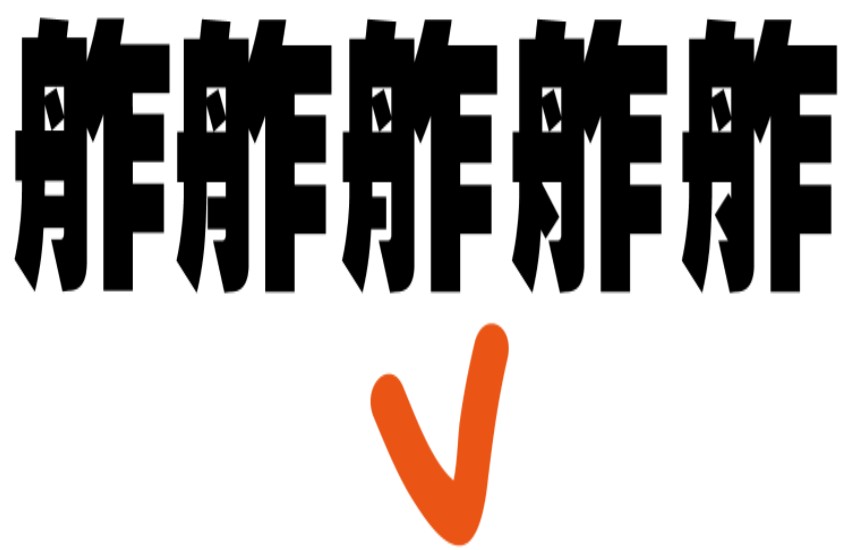
逐浪经典粗黑体
作品设计背景与理念
逐浪经典粗黑体是一种基于现代汉字简体设计的字体,力求创造一种特粗黑体。
我们看到市面上的粗黑体有以下问题:
1. 粗壮而无细节,缺乏韵的美;
2. 违反中国书法的传统原则;
3. 可选空间较少,甚至形成了“粗就是丑”、“丑必然粗”的悖论。
于是逐浪软件人启动了本字库的研发。
设计本字库时,我们确定了字体(库)研发八步原则:
1、选样本
2、建规则
3、创模板
4、开工厂
5、勾字形
6、导字库
7、发软件
8、测版面
与传统粗黑字体相比,逐浪经典粗黑体的特色细节包括:
左边“又”字、反文旁的字,最后一笔角度拉大,使之更有力量。
红等左绞丝旁,左边拉窄、右边拉宽,略上迎姿势。
竖提,改为尖角、倒三角形,下方角度为上坚线中间。
勾笔多采用收三角方法,从而在方形之间有尖锐之感。
永,第一点应平,国内同类字库普遍受日系字体影响很大,往往永字采用右上角对角相似,并不具备完美。
舟字旁下笔画故意开笔,避免档到水口,合中国之美,有聚财之德(规避旧字吐舌如僵尸之丑)